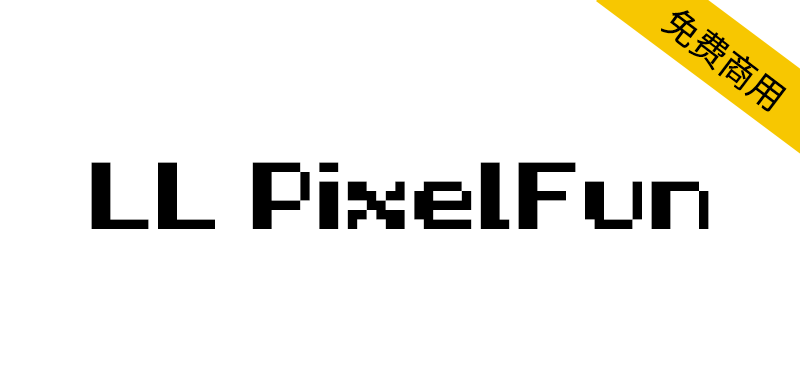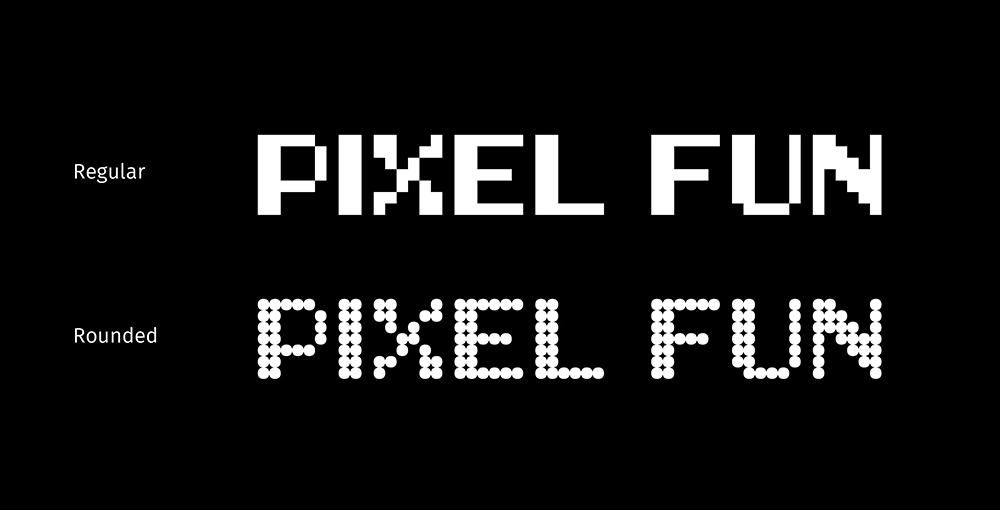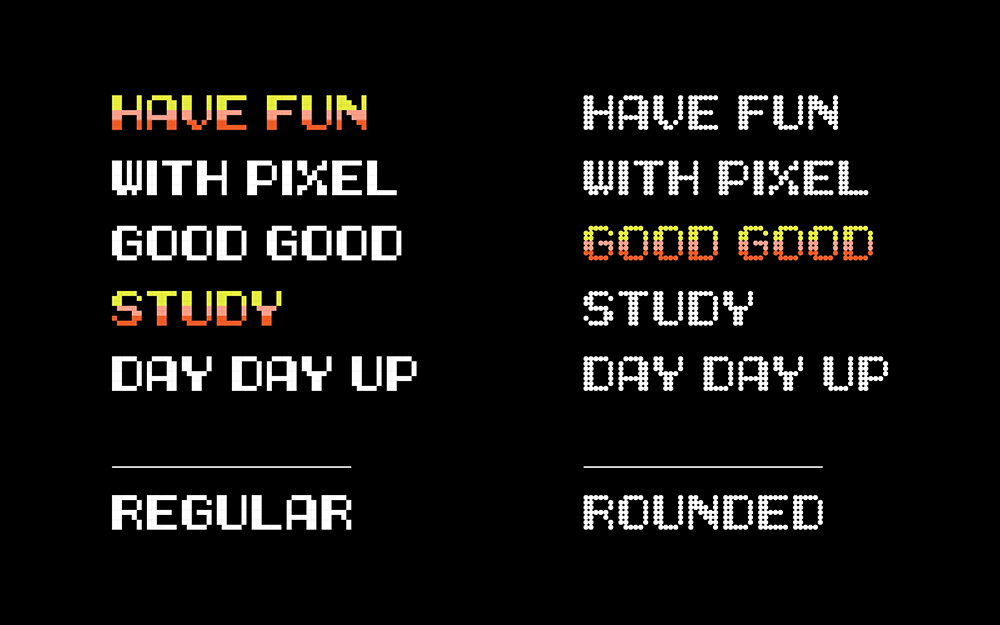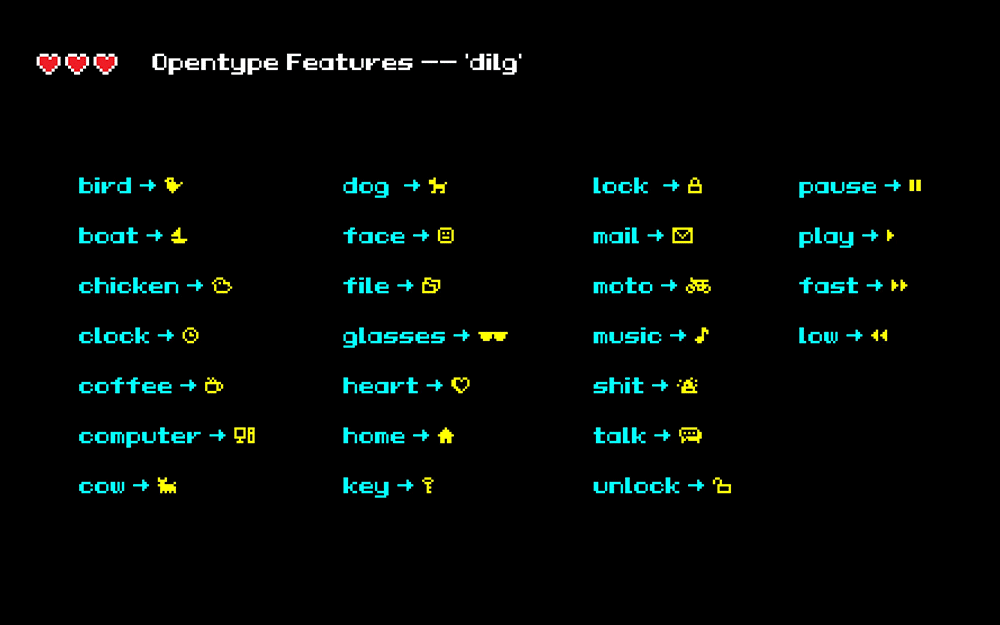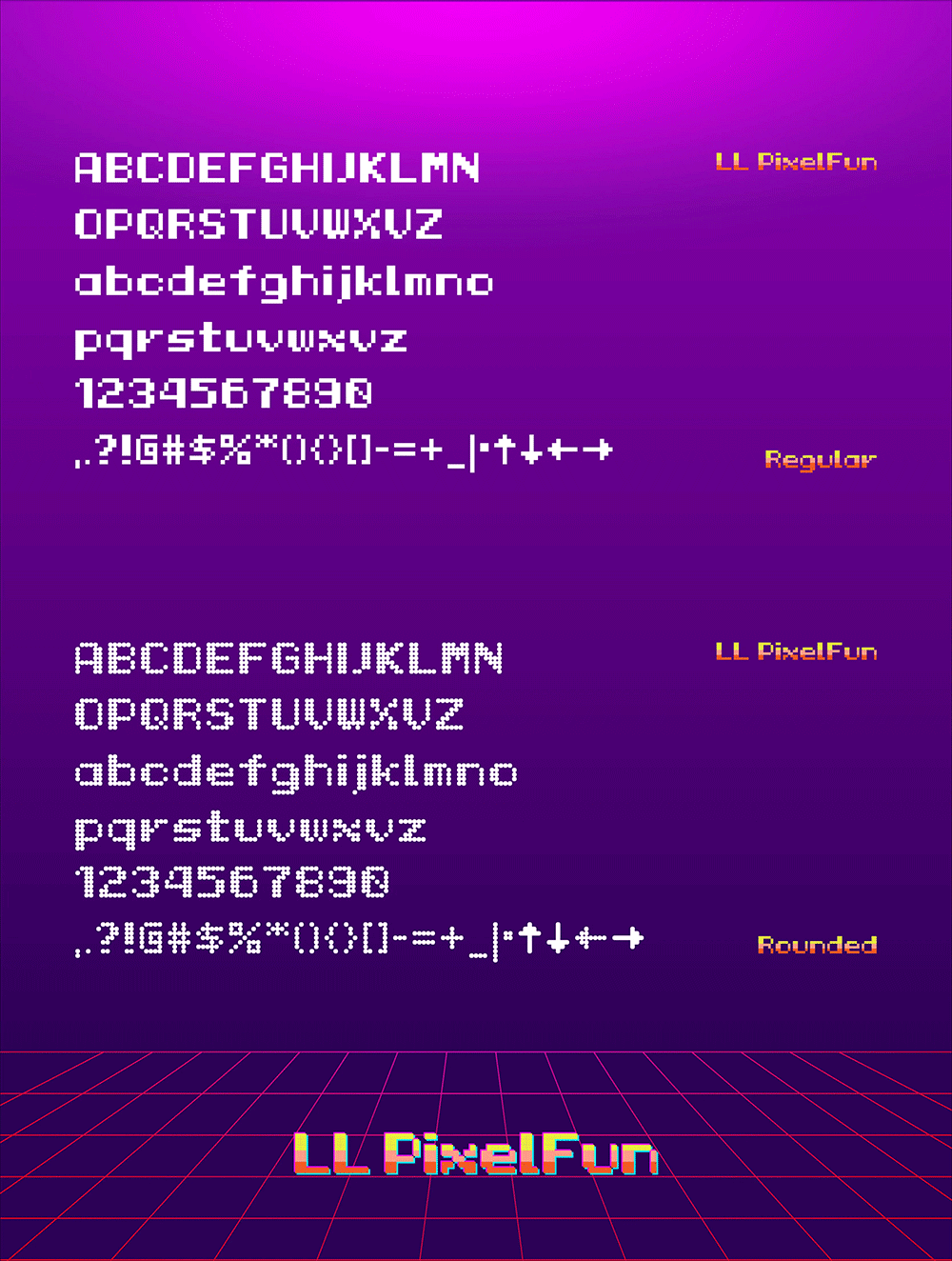
LL PixelFun 是一款复古电子像素风格的西文字体,有两种风格类型,一种是方块常规体,另一种是以点阵状风格,整体轮廓清晰、色彩鲜明,非常适用于像素机能风,故障风、赛博朋克风等设计场景。
为了增加字体的可玩度,加入自由合字的特性,输入以下单词:
bird boat chicken clock coffee computer cow dog face fast file glasses heart home key lock low mail moto music pause play shit stop talk unlock
在Ai或者Ps中Opentype工具栏点击自由连字即可生成相对应Icon(无聊的小功能)